2024년 코더를 위한 9가지 최고의 글꼴(순위)
코더를 위한 글꼴은 단순한 선호 그 이상입니다. 이는 프로그래밍의 명확성, 가독성 및 전반적인 효율성을 위해 필수적입니다. 올바른 글꼴을 사용하면 눈의 피로가 크게 줄어들고 코딩 과정이 더 부드럽고 빨라질 수 있습니다.
최근 몇 년 동안 개발자와 프로그래머가 심미적 매력과 실용적인 기능을 제공하는 글꼴을 찾는 가운데 코더를 위한 최고의 글꼴을 선택하려는 노력이 점점 더 대중화되고 있습니다.
코더를 위한 최고의 글꼴 9가지
1. 피라 코드
최적의 용도: 내장 합자
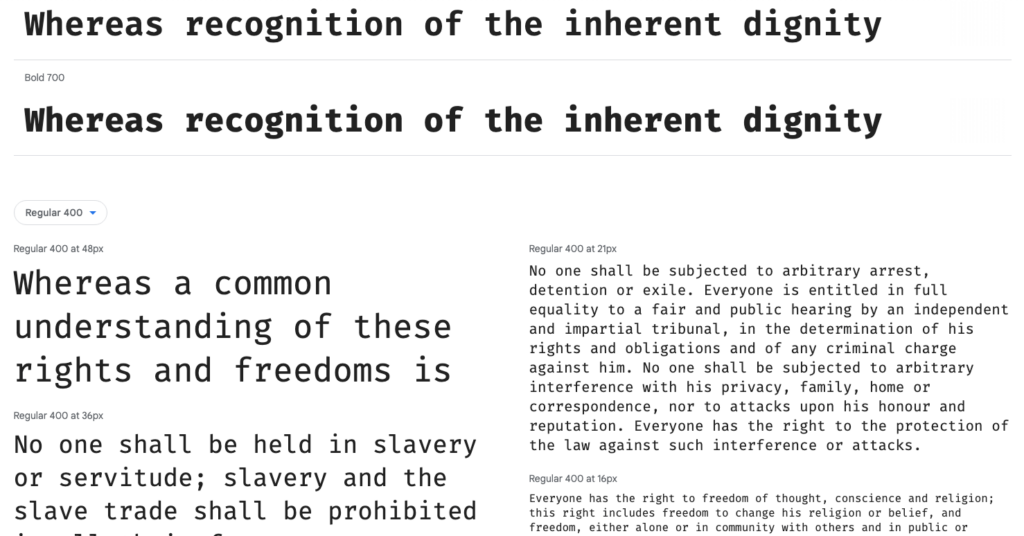
Fira Code는 가독성과 효율성에 대한 독특한 접근 방식으로 인해 코더를 위한 최고의 글꼴 중 하나로 돋보입니다. 이 글꼴은 여러 문자를 더 읽기 쉬운 단일 기호로 결합하는 프로그래밍 합자를 활용합니다. 예를 들어 => 와 같은 일반적인 시퀀스가 하나의 매끄러운 글리프에 병합되어 코드를 한 눈에 더 쉽게 읽고 이해할 수 있습니다.
현대 코더를 염두에 두고 설계된 Fira Code는 미적 측면뿐만 아니라 프로그래머의 인지 부하를 줄이는 데에도 중점을 두고 있습니다.
일반적인 프로그래밍 기호와 문자를 단순화함으로써 특히 긴 코딩 세션 중에 잘못된 해석과 오류를 최소화하는 데 도움이 됩니다. 이 기능은 이러한 연산자를 많이 사용하는 언어로 작업하는 개발자들 사이에서 인기 있는 선택입니다.
코딩 글꼴에 합자를 통합하는 것은 상대적으로 새로운 추세이며 Fira Code는 대부분의 코딩 요구 사항을 충족하는 포괄적인 합자 세트를 제공하는 선두에 있습니다. 다양한 IDE와 텍스트 편집기에서 널리 채택되고 있다는 것은 코딩 커뮤니티 내에서 그 기능과 인기를 입증하는 것입니다.
2. 소스 코드 프로
최적의 용도: 전문 개발 환경
Source Code Pro는 Adobe에서 코더를 위해 특별히 디자인한 글꼴로 유사한 문자( O 와 0 또는 { 와 ( ) 등)를 쉽게 구별할 수 있다는 점을 강조했습니다. 가중치가 넓어 다양한 코딩 환경과 개인 취향에 맞게 적용할 수 있습니다. 모든 개발자가 자신의 요구에 맞는 완벽한 설정을 찾을 수 있도록 보장합니다.
이 글꼴의 고정폭 디자인은 코드의 가독성을 위해 맞춤 제작되어 눈에 과도한 피로를 주지 않으면서 오랜 시간 동안 프로그래밍을 할 수 있도록 해줍니다. 다양한 문자와 기호를 지원하므로 여러 프로그래밍 언어로 작업하는 국제 코딩 프로젝트 및 개발자에게 적합합니다.
Source Code Pro의 명확성과 단순성은 오류를 줄이고 코딩 효율성을 향상시키는 데 도움이 되므로 코딩 환경에서 기능과 가독성을 우선시하는 전문 개발자들 사이에서 선호되는 선택이 됩니다.
3. JetBrains 모노
최적의 용도: 향상된 독서 경험
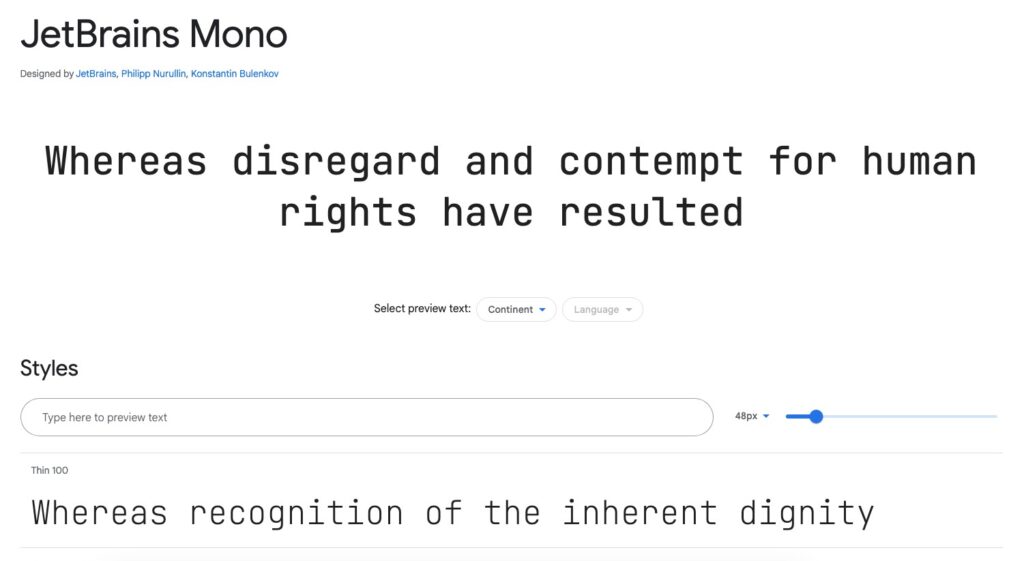
코딩 글꼴 제품군에 비교적 새롭게 추가된 JetBrains Mono는 개발자의 읽기 환경을 개선하는 데 중점을 두고 만들어졌습니다. 문자 간격과 높이가 증가하여 가독성이 크게 향상되고 눈의 피로가 줄어듭니다.
JetBrains Mono의 주목할만한 측면 중 하나는 최적화된 문자 너비로, 문자를 더욱 균일하게 정렬하고 코드를 더 쉽게 따라갈 수 있게 해줍니다. 또한 이 글꼴에는 Fira Code와 유사하게 코딩을 위해 특별히 설계된 다양한 합자가 포함되어 있어 코드를 보다 읽기 쉽고 컴팩트한 형식으로 표시하는 데 도움이 됩니다.
가장 인기 있는 일부 IDE 제작자가 개발한 JetBrains Mono는 코딩 환경에 원활하게 통합되어 편안함이나 가독성을 희생하지 않고 코딩의 시각적 측면을 향상시키는 맞춤형 환경을 제공합니다.
4. 콘솔라
최적의 대상: Windows 사용자
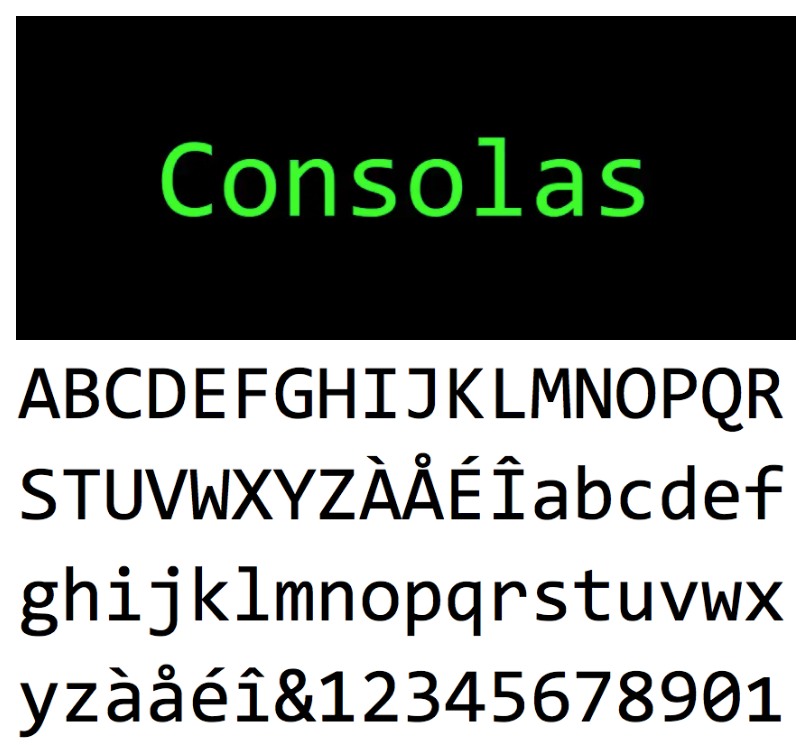
Consolas는 코딩을 위해 명확하고 읽기 쉬운 글꼴이 필요하다는 Microsoft의 대답이며 Windows 운영 체제에 포함되어 있습니다. 특히 가독성이 뛰어나 Windows 사용자들에게 많은 사랑을 받고 있으며, ClearType과 잘 작동하도록 설계되어 LCD 화면의 텍스트 선명도를 높여줍니다.
이 글꼴은 중앙에 점이 있는 0(영)과 코딩 실수를 방지하는 데 중요한 문자 O와 같이 비슷한 문자 사이의 균형 잡힌 간격과 차별화가 돋보입니다. Consolas는 광범위한 프로그래밍 환경과 언어를 지원하므로 개발자가 다양한 선택을 할 수 있습니다.
Consolas의 명확하고 깔끔한 라인과 고정 폭 특성을 통해 코드를 쉽게 스캔할 수 있어 프로그래머가 구문과 구조를 빠르게 식별할 수 있습니다. 광범위한 가용성과 Windows IDE와의 통합으로 인해 코딩 작업 공간의 효율성과 명확성을 중시하는 많은 개발자가 선호하는 글꼴이 되었습니다.
5. 로보토 모노
최적의 용도: 플랫폼 전반에 걸친 다양성
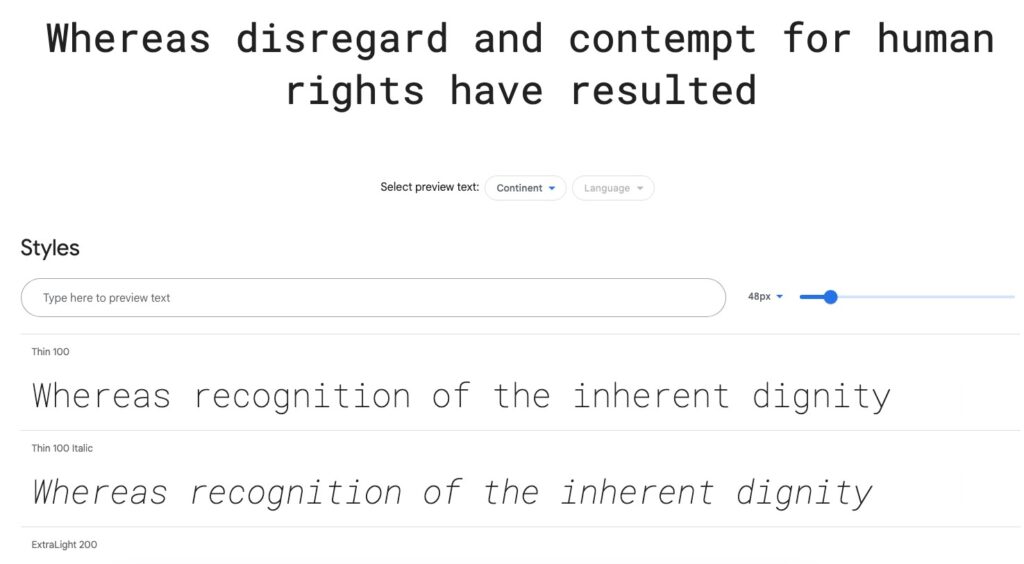
Roboto Mono는 Google이 Android 인터페이스용으로 개발한 이후 다양한 플랫폼에서 인기를 얻은 Roboto 글꼴 계열의 일부입니다. Roboto 제품군의 다른 제품과 동일한 기계적 골격을 공유하지만 코딩 및 고정 폭 텍스트 요구 사항에 맞게 특별히 설계되었습니다.
친근하고 개방적인 곡선을 갖춘 Roboto Mono는 다른 많은 고정 폭 글꼴보다 덜 경직되고 더 접근하기 쉬운 느낌을 줍니다. 이러한 품질은 코딩에 오랜 시간을 소비하고 가독성을 저하시키지 않으면서 눈에 편한 글꼴이 필요한 사람들에게 이상적입니다.
Roboto Mono의 균일성과 문자 간격은 세심하게 균형을 이루어 코드의 가독성을 향상시켜 모바일 및 데스크톱 개발 환경 모두에 탁월한 선택입니다. 플랫폼과 환경 전반에 걸친 호환성과 오픈 소스 특성 덕분에 모든 개발자의 작업 흐름에 쉽게 통합될 수 있습니다.
6. 데자부 산스 모노
최적의 용도: 폭넓은 문자 지원
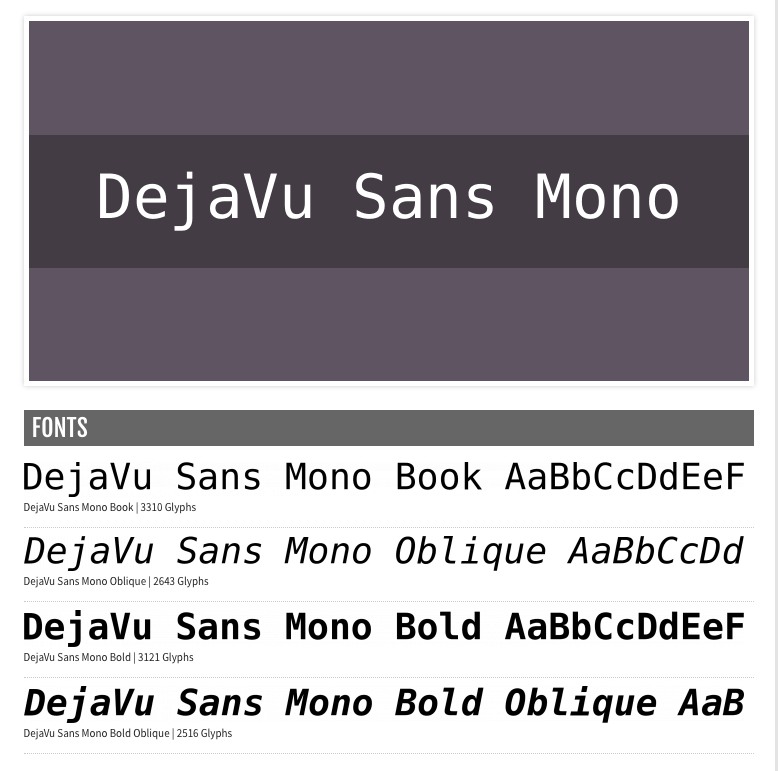
DejaVu Sans Mono는 광범위한 문자 세트 범위로 유명한 DejaVu 글꼴 제품군의 일부입니다. 이 글꼴은 유니코드 문자를 폭넓게 지원하므로 코더들 사이에서 높은 평가를 받고 있으며 국제 프로젝트나 다양한 기호 및 알파벳 세트가 필요한 모든 작업에 탁월한 선택입니다.
명확성과 쉬운 가독성에 초점을 맞춘 DejaVu Sans Mono는 구별 가능한 0 (영)과 O (대문자 o), 코딩 정확도에 중요한 { ( 괄호) 등 잘 구분된 문자를 제공합니다. 균형 잡힌 간격과 라인 높이는 긴 코딩 세션 동안 눈의 피로를 줄이는 데 도움이 됩니다.
이 글꼴은 다용성과 광범위한 호환성으로 인해 다국어 환경에서 작업하거나 광범위한 수학 또는 기술 기호가 포함된 프로젝트에서 작업하는 개발자가 선호하는 선택입니다. 또한 오픈 소스 라이선스를 통해 모든 프로젝트에서 자유롭게 사용하고 배포할 수 있습니다.
7. 해킹
최적의 용도: 맞춤화 가능성
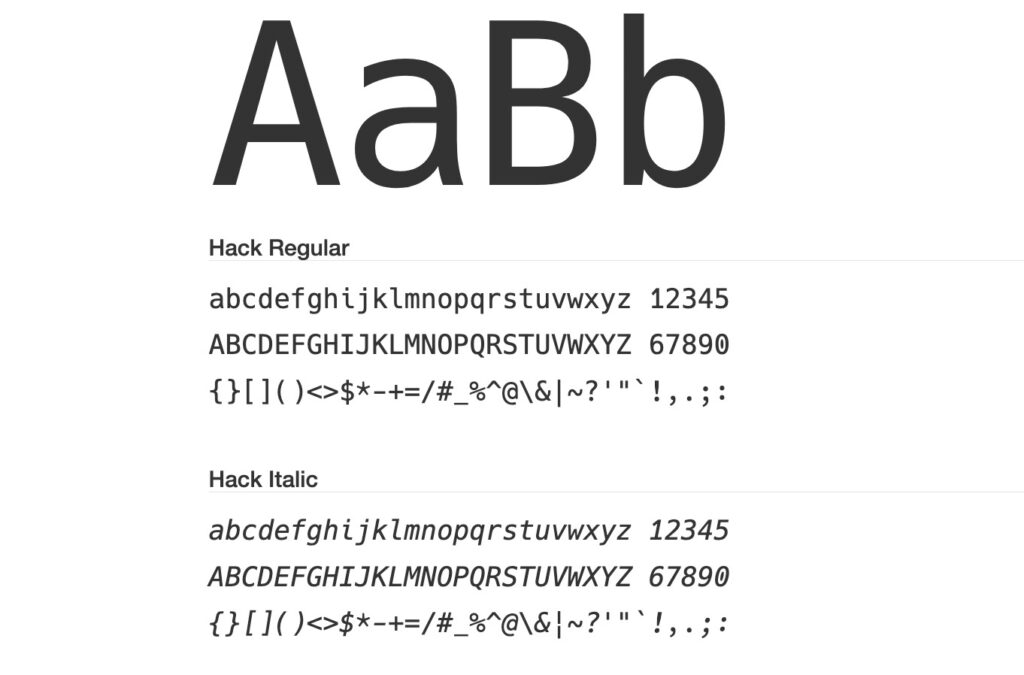
Hack은 코더의 실제 요구 사항에 중점을 두고 설계되었으며 명확하고 간결한 문자 표현과 함께 높은 수준의 사용자 정의 기능을 제공합니다. 0과 문자 O를 구별할 수 있는 문자 모양이 특징이며, 다양한 디스플레이와 해상도에서 가독성이 최적화되었습니다.
Hack을 차별화하는 점은 개발자가 정확한 사양에 맞게 글꼴을 사용자 정의하고 조정할 수 있는 오픈 소스 특성입니다. 이러한 적응성은 Hack을 코딩 환경에 대한 특정 요구 사항이나 선호도가 있는 사람들에게 특히 매력적으로 만듭니다.
Hack의 디자인은 문자 너비와 간격 사이의 균형을 강조하여 코드를 쉽게 스캔할 수 있고 미적으로 보기에도 좋습니다. 코딩 경험을 개선하려는 노력은 지속적으로 개선과 업데이트를 위해 노력하는 글꼴 주변의 활발한 커뮤니티에서 분명하게 드러납니다.
8. 인콘솔라타
최적의 용도: 오픈 소스 프로젝트
Inconsolata는 다양한 크기와 해상도에서 선명하고 명확한 가독성으로 오픈 소스 커뮤니티에서 높이 평가되는 글꼴입니다. Raph Levien이 디자인한 이 글꼴은 Consolas 및 기타 고전적인 고정폭 글꼴에서 영감을 얻었지만 더 넓고 개방적인 느낌으로 많은 개발자가 긴 코딩 세션 중에 눈이 편하다고 생각합니다.
이 글꼴은 코딩에 필요한 정밀도를 유지하면서 눈의 피로를 줄이는 것을 목표로 하는 현대적이고 깔끔한 디자인으로 차별화됩니다. 문자는 명확하고 구별 가능하도록 설계되어 유사한 기호를 잘못 읽어서 발생하는 일반적인 코딩 오류를 방지하는 데 도움이 됩니다.
오픈 소스 세계에서 Inconsolata의 인기는 부분적으로 많은 코드 편집기 및 IDE에 포함되어 있을 뿐만 아니라 SIL Open Font License에 따라 무료로 제공되기 때문입니다. 따라서 오픈 소스 프로젝트를 진행하는 개발자나 코딩 환경을 위한 고품질, 무료 옵션을 찾는 개발자가 접근할 수 있는 선택이 됩니다.
9. PT 모노
최적의 용도: 텍스트가 많은 코딩
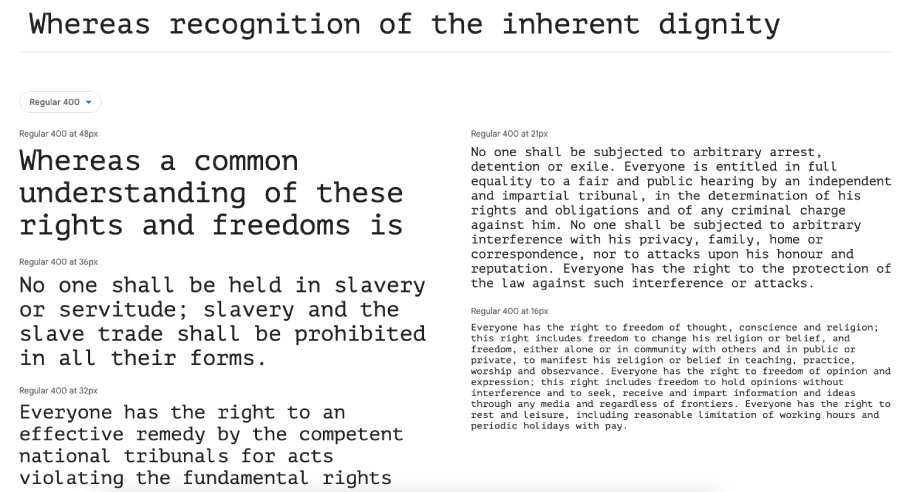
PT Mono는 고정폭 텍스트가 널리 사용되고 가독성이 가장 중요한 환경에서 사용하도록 설계되었습니다. PT Sans, PT Serif를 포함하는 PT 글꼴군에 속하며 화면 가독성이 뛰어난 것으로 알려져 있습니다.
정확한 문자 모양과 충분한 간격을 갖춘 PT Mono는 텍스트가 많은 코드의 가독성을 향상시키는 것을 목표로 합니다. 따라서 대규모 코드 블록이나 복잡한 알고리즘을 사용하여 작업하고 작업을 빠르게 탐색하고 이해해야 하는 개발자에게 이상적인 선택입니다.
PT Mono는 또한 코딩 정확도에 중요한 측면인 비슷한 모양의 문자 간의 강력한 차별화 기능을 제공합니다. 광범위한 언어 및 기호에 대한 가용성과 지원으로 인해 국제 코딩 프로젝트 또는 높은 가독성이 요구되는 모든 애플리케이션에 다양한 선택이 가능합니다.
결론
올바른 글꼴을 선택하는 것은 미적인 측면뿐만 아니라 생산성을 유지하고 긴 코딩 세션 동안 편안함을 보장하기 위해 코더에게 매우 중요합니다. 다양한 옵션이 제공되므로 몇 가지를 실험해 보고 귀하의 요구에 가장 적합한 옵션을 찾는 것이 좋습니다.